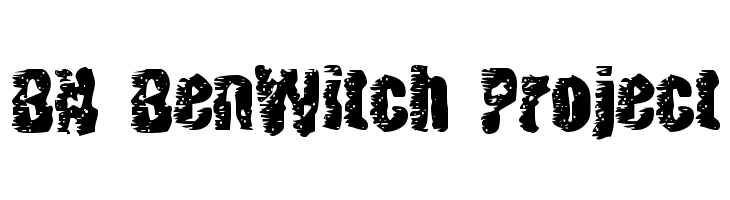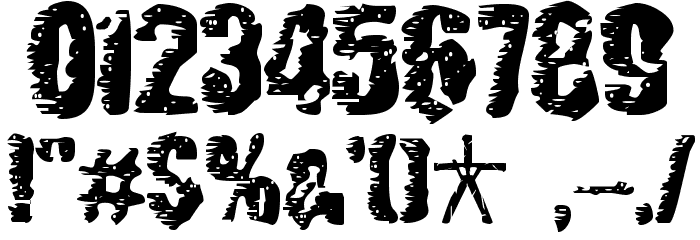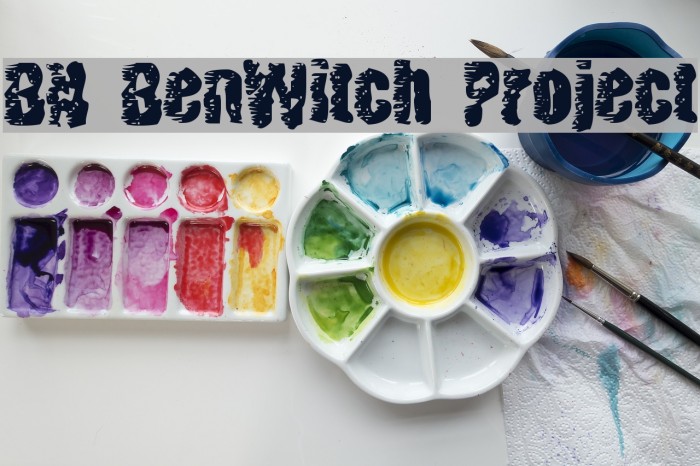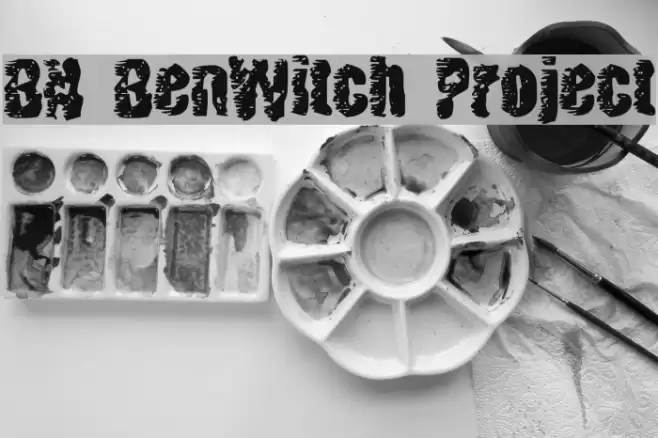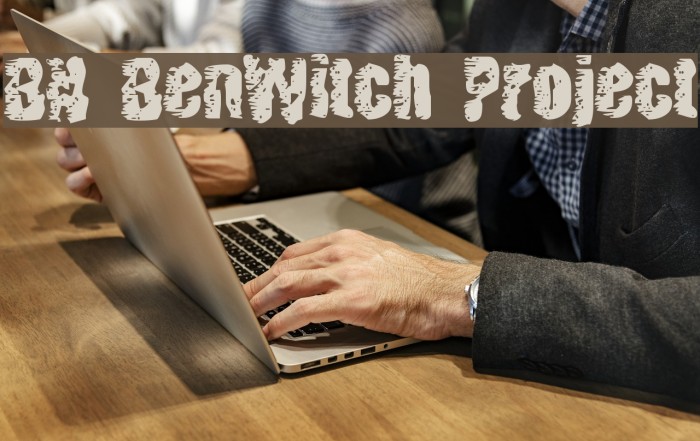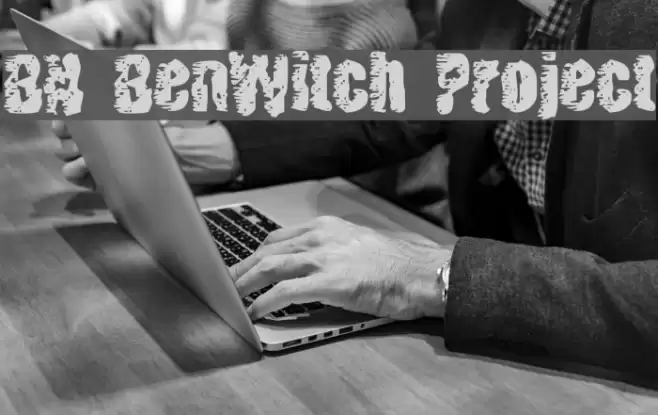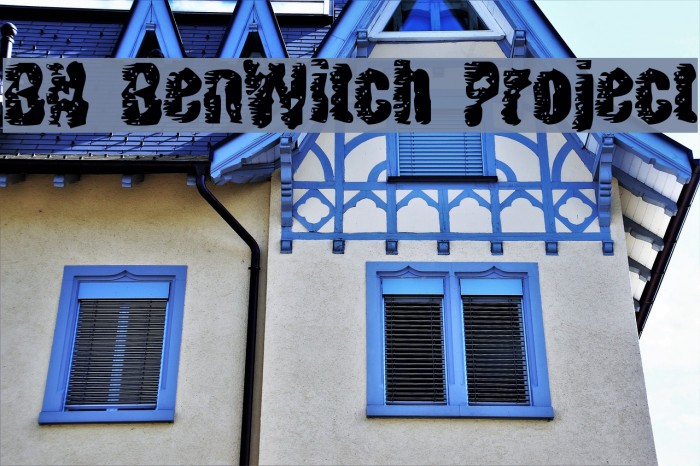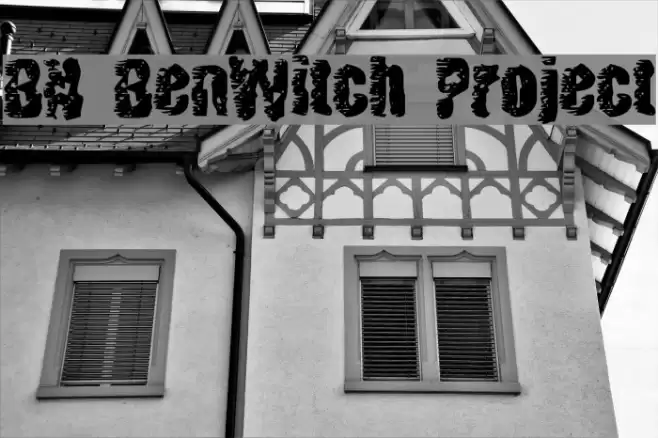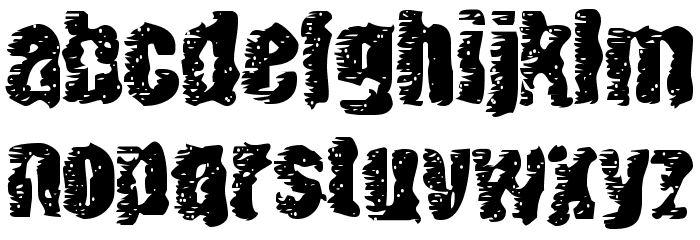
BN BenWitch Project Font
CategoriasDistorted Eroded
NegritoYes
ItálicoNo
LarguraNormal
Espaçamento de caracteresMonospaced
ContrasteLow
Estilo geralDecorative
Caso de usoHeadlines, Posters, Logos
Projetos propostosPerfect for horror movie posters, Halloween event flyers, edgy album covers, or any project needing a dramatic, grunge aesthetic.